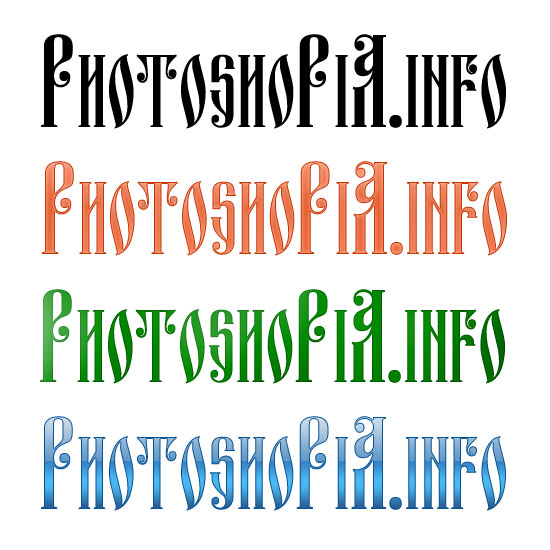
Красивые русские шрифты для Ворда и Фотошопа
Встречайте очередное масштабное пополнение раздела красивых шрифтов где я собираю все соответствующие подборки. В отличии от других заметок с материалами здесь дополнительно будут представлены пояснения по процессу их установки в Ворде (и заодно Фотошопе).Заметка пригодится пока я работаю над обновлением поста о красивых русских шрифтах. Решил немного развить эту тему т.к. на прошлую статью часто заходят из поиска по фразам похожим на «красивые шрифты для word» или «где найти русские шрифты для ворда«. А ведь там нет вообще никакой информации по данному текстовому редактору! Поэтому и придумал сочинить отдельный пост, дополнив его ответами на вопросы пользователей.
Заметка состоит из нескольких частей. Если вы что-то уже знаете, можете смело промотать текст дальше, непосредственно к подборкам.
Необычный вид текстов в Ворде может использоваться, например, для разного рода торжественных документов (тех же поздравлений, грамот).
Красивые шрифты для Word
Вообще, конечно, красота — понятие субъективное, особенно когда речь идет о дизайне. Я лично старался выбирать красивые шрифты для Word, которые бы сам использовал в работе. В подборке всего 10 вариантов (зато бесплатных), скачать их можете, перейдя по ссылке.
После тестирования некоторых решений, заметил еще один нюанс. Какой бы красивый шрифт в Ворде вы не выбрали, он должен быть простым и понятным для читателя, поскольку у вас все же документ, а не графическая иллюстрация. Это в Фотошопе можно применить разные эффекткы оформления, в текстовом редакторе, как правило, выделения и стили более-менее простые.
Тут скорее важна практичность.
Barkentina
NeSkid (Comica BD)
Gecko
m_Acadian
Docker Three
Anime Ace v3
FoglihtenNo06
MerriWeather
ZnikomitNo25
Bulgaria Moderna V3 font
Рукописные русские шрифты для Ворда
Лучше всего для текстового редактора подходят, конечно, рукописные фонты, т.к. они соответствуют стилистике написания документов, писем, заметок. Тут вам не фотошоп дабы экспериментировать с гранжевыми, готическими надписями 🙂 Хотя рукописные шрифты для Word также могут иметь разное оформление, отличаясь друг от другая определенными нюансами: аккуратностью письма, отступами между буквами, жирностью линий и т.
п.
Nautilus
Good Vibes Pro
Liana
Pecita
Gunny Rewritten
Wolgast Two Font Family
Не обращайте внимание на примеры, где используются англоязычные тексты — они взяты с сайтов источников. Все эти 3 варианта — полноценные русские шрифты для Word (можете сами проверить).
Azbuka03_D
Denistina
Katherine
Shlapak Script